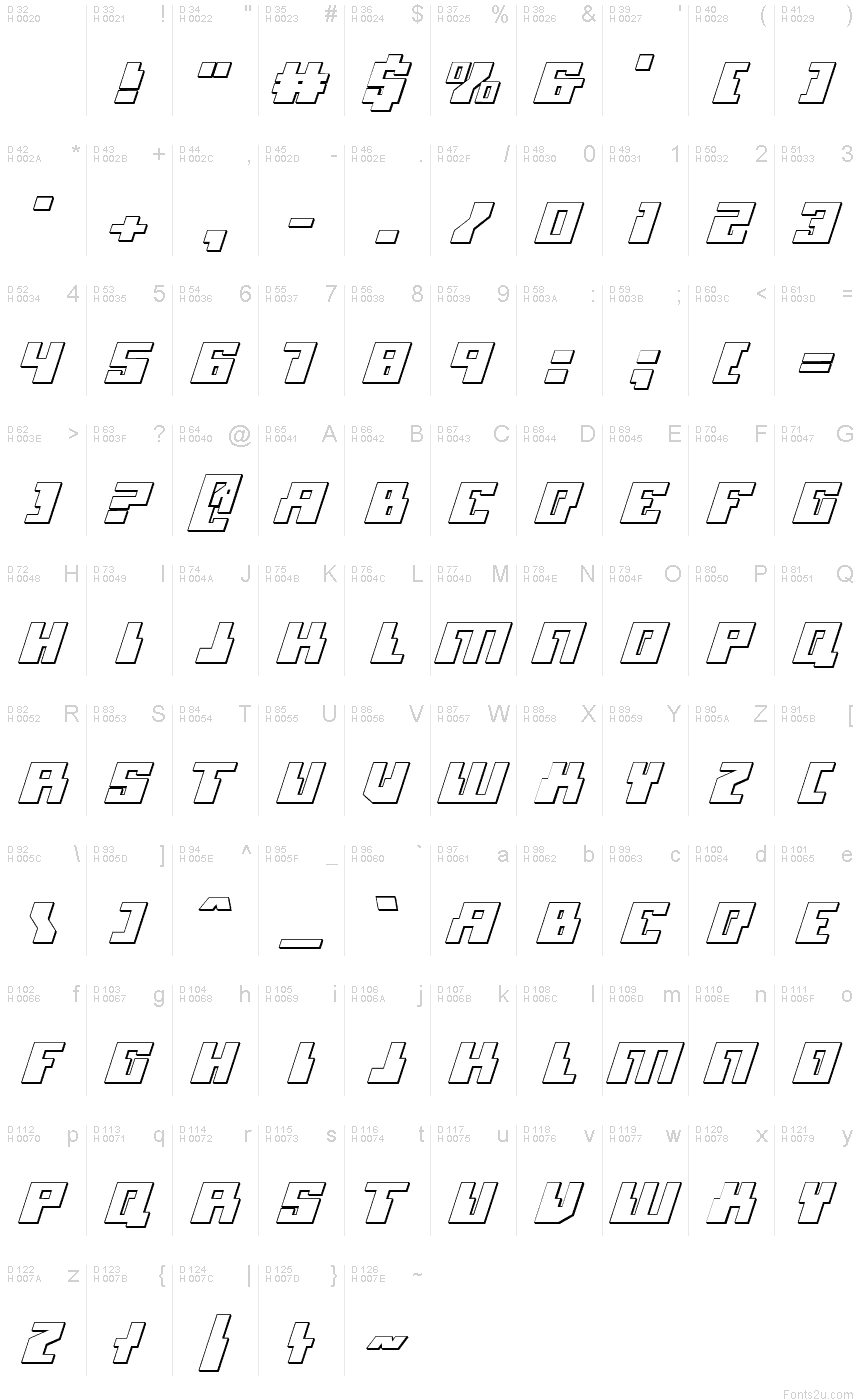
Micronian 3D Italic, entworfen von Iconian Fonts, ist eine kostenlose, futuristische Display-Schrift mit breiten, nach vorne geneigten Buchstaben. Scharfe Ecken, quadratische Öffnungen und versetzte Innenlinien verleihen dem Schriftbild einen maschinellen, dreidimensionalen Aufbau.
Sie kann einen Spieletitel in ein Interface-Element verwandeln. Dieselbe eckige Konstruktion eignet sich für Science-Fiction-Poster, Esports-Branding und Technik-Verpackungen, bei denen die umrissenen Formen Raumschiffpaneele, Leiterbahnen oder abgeschrägte Produktgrafiken widerspiegeln können.